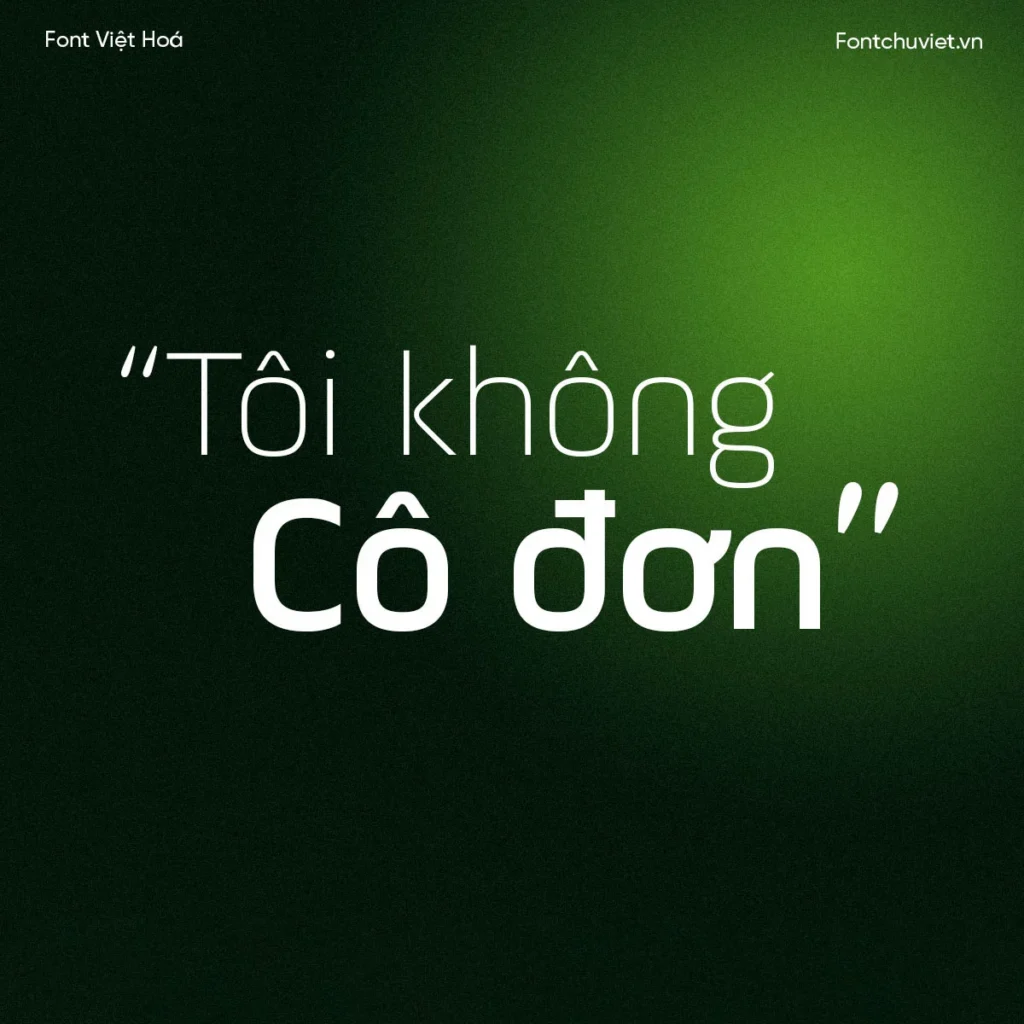
2 Font VL Ample – Font Việt hoá là lựa chọn hoàn hảo cho thiết kế với 2 phiên bản Regular và Bold. Font có thiết kế không chân, các gốc bo tròn nên tạo cảm giác mềm mại.
Ưu Điểm Của 2 Font VL Ample – Font Việt hoá
Font VL Ample – Font Việt hoá phù hợp cho nhiều loại thiết kế, từ tiêu đề đến nội dung.
Phiên Bản Regular
Phiên bản Regular của Font VL Ample – Font Việt hoá phù hợp cho phần nội dung.
Phiên Bản Bold
Phiên bản Bold của Font VL Ample – Font Việt hoá phù hợp cho tiêu đề.
Lợi Ích Của 2 Font VL Ample – Font Việt hoá
2 Font VL Ample – Font Việt hoá mang lại nhiều lợi ích cho thiết kế, bao gồm:
- Tạo cảm giác mềm mại
- Phù hợp cho nhiều loại thiết kế